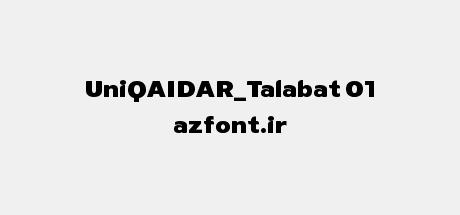
UniQAIDAR_Talabat 01
فونت زیبای رایگان UniQAIDAR_Talabat 01
قلم زیبای UniQAIDAR_Talabat 01 از سری قلم های بسیار زیبا برای تایپوگرافی و لوگو تایپ می باشد.این قلم در وزن Regular و توسط Dalton Maag Ltd طراحی و منتشر شده است.